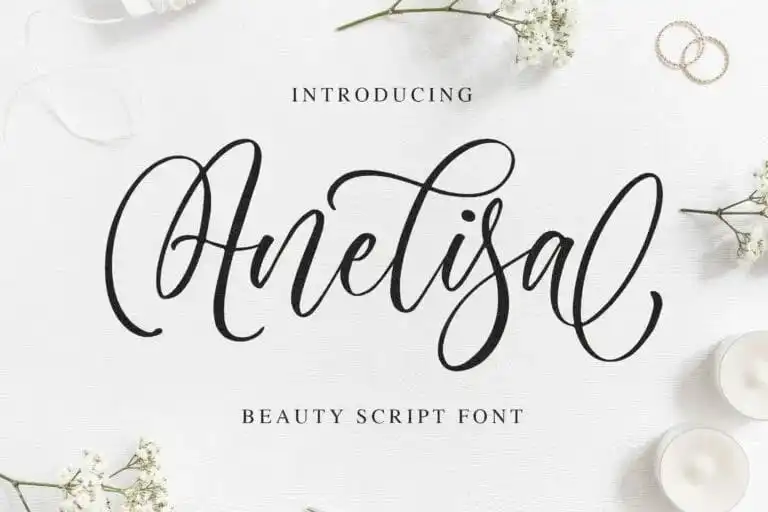
Anelisa Calligraphy Font – Download Grátis
Anelisa Calligraphy Font é uma fofa e desafiada fonte de script que traz a essência única da calligrafia cascateira para seu projeto. Com estilos únicos de letras decorativas, esta fonte tem um estilo moderno cheio de vida e graça, perfeitamente adaptável à variedade de usos imagináveis. Essa font foi criada pelo Designer 99designs Blankids em homenagem ao popular estilo de script atual. A Anelisa é uma excelente escolha para quem procura trazer um toque divertido e único a seus projetos. Suas cores vivas, estilos decorativos e base que parece dançar criam um design imersivo e envolvente. Perfeita tanto para exibições visuais quanto para criações de arte como roupas ou cartões personalizados, você pode usar essa font para criar frases de citação bonitas, logotipos memoráveis ou até mesmo assinaturas em sua decoração. Com Anelisa Calligraphy Font, você tem a chance de transformar qualquer design com uma pitada moderna e divertida do mundo da calligrafia. Seja para um desafio de criação em 99designs ou para personalizar seu próximo projeto, é um tesouro que vale cada centavo.